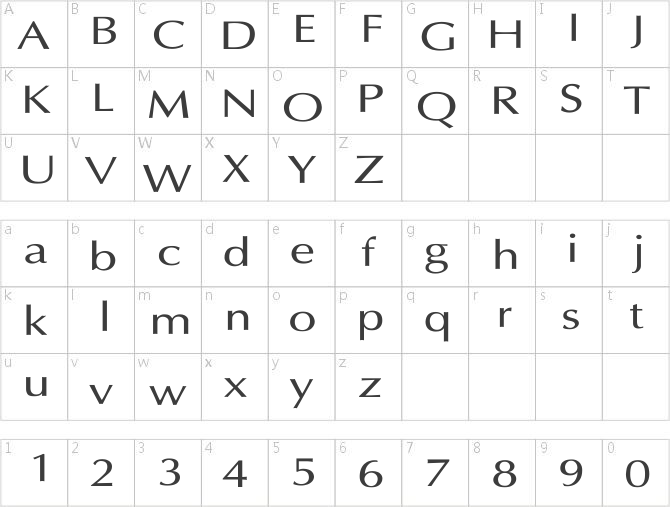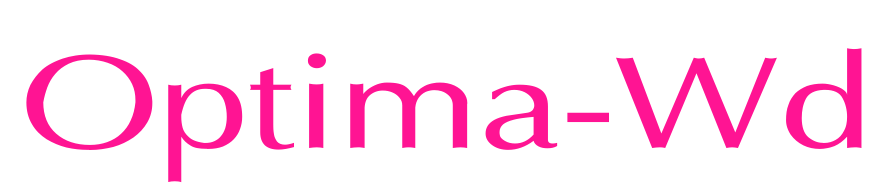
Optima-Wd 詳情頁(yè)
Optima-Wd字體字庫(kù)是一款讓人賞心悅目、百看不厭的英文字體,適合各類(lèi)廣告和產(chǎn)品包裝設(shè)計(jì)應(yīng)用,字體大小0.05MB,格式為ttf字體,上傳用戶(hù)是 造物設(shè)計(jì)師,作者/版權(quán)方為未知